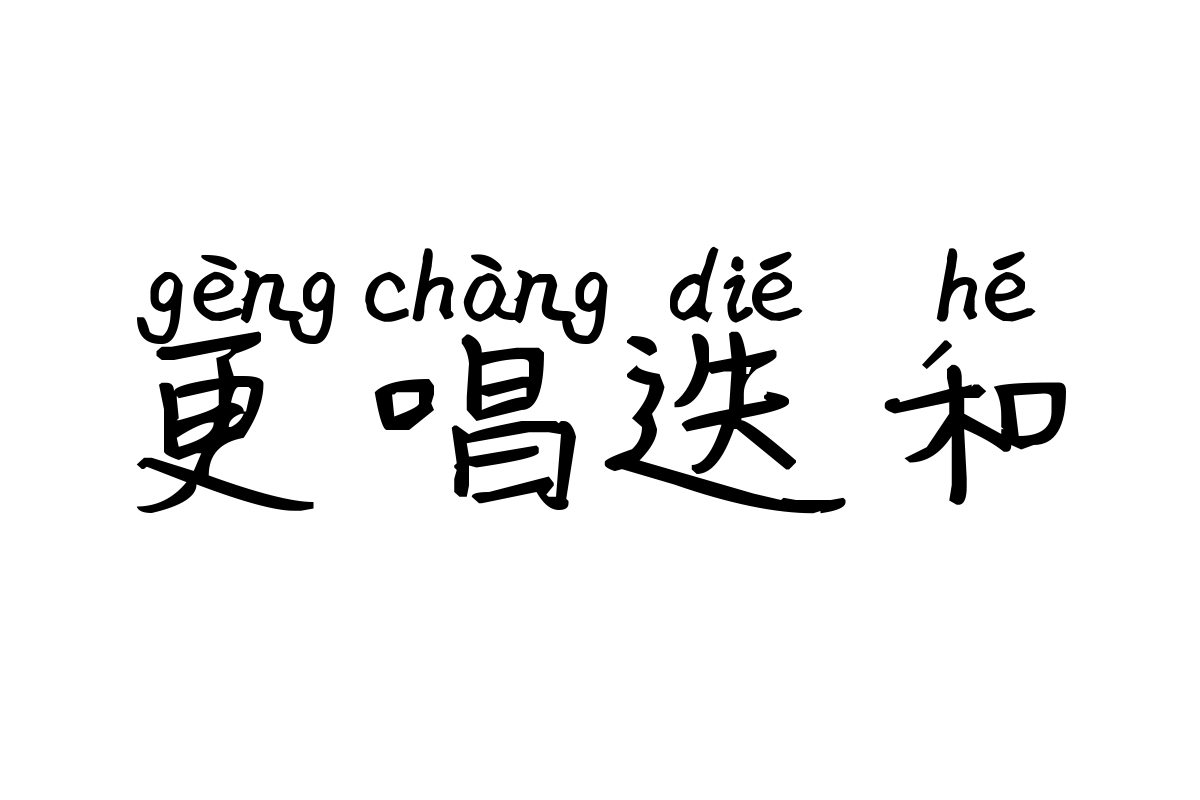
米开街角的小浪漫拼音体是一种具有独特风格的中文字体,它结合了现代和传统元素。这种字体的特点是在保持传统书法笔触的基础上,加入了现代设计的元素,使得字体既有古典韵味又不失时尚感。
米开街角的小浪漫拼音体的主要特点是其独特的字形结构。这种字体的笔画粗细不一,既有粗犷豪放的一面,又有细腻柔美的一面,给人一种既大气又精致的感觉。此外,这种字体还采用了一些现代的设计元素,如不规则的笔画、曲线等,使得整体效果更加独特和新颖。
总的来说,米开街角的小浪漫拼音体是一种非常独特的中文字体,它既有传统的韵味,又有现代的时尚感,适合用于各种需要强调个性和创意的场合。